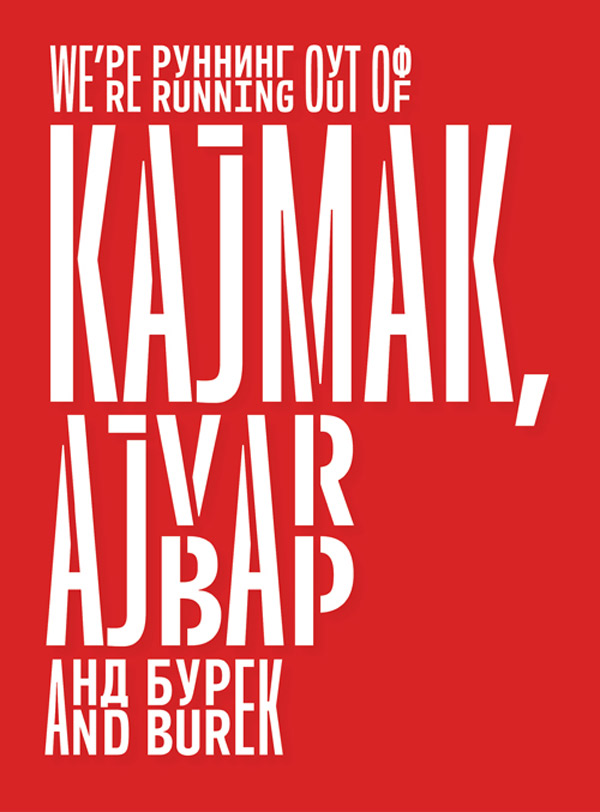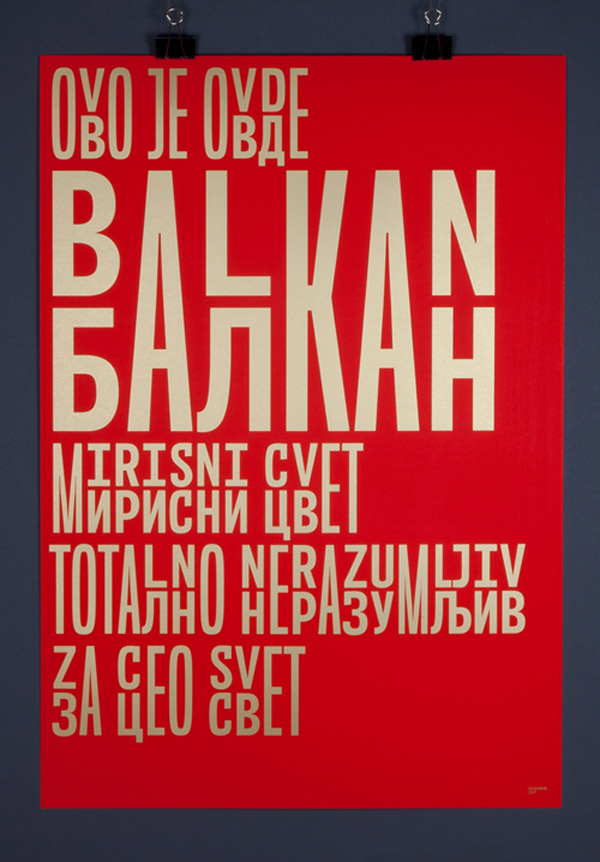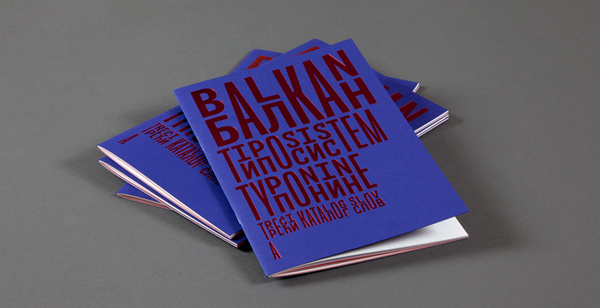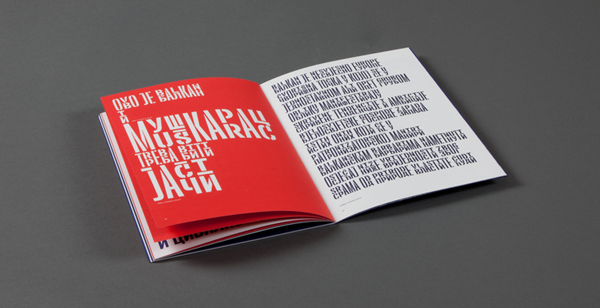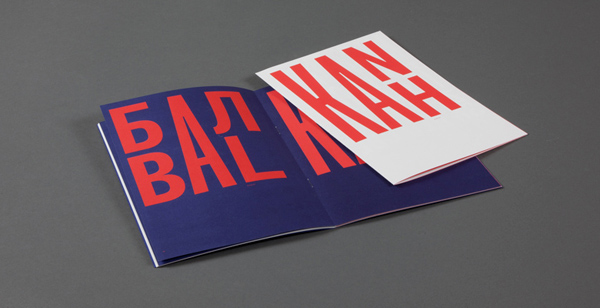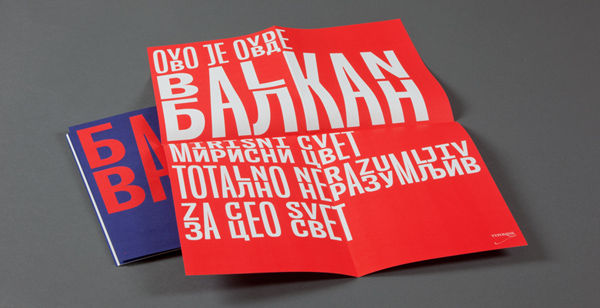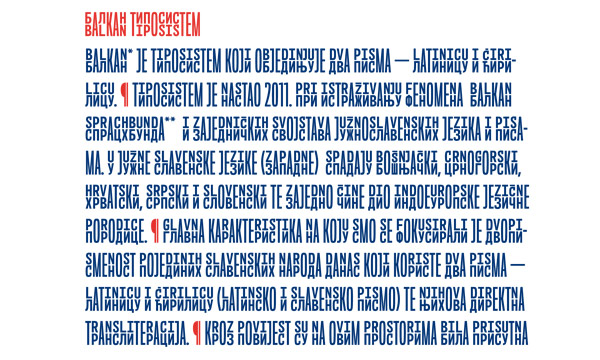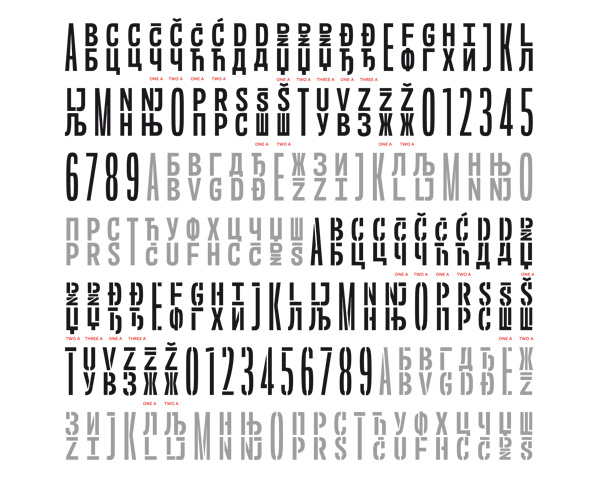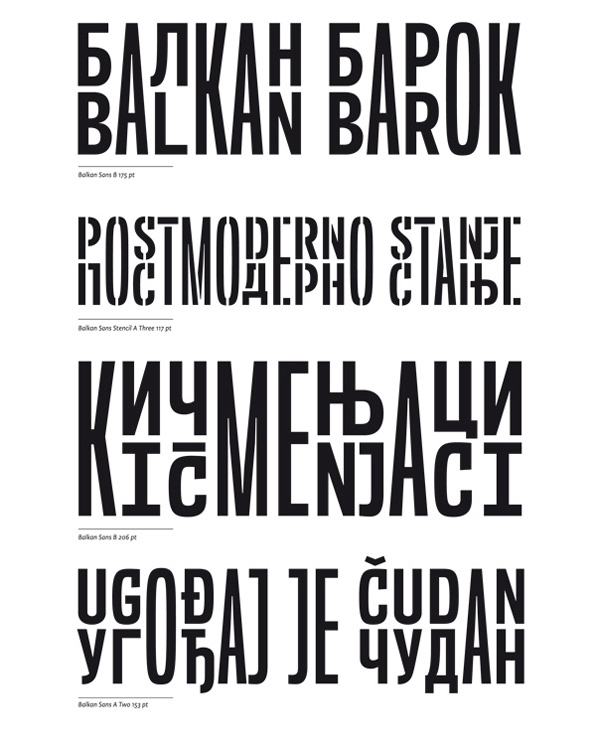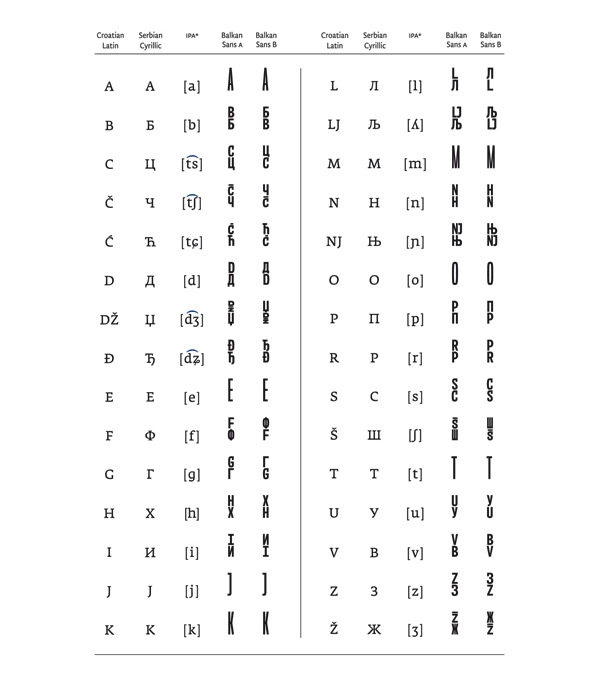
La península de los Balcanes es un territorio habitado por un crisol de etnias, culturas y religiones cuya incomprensión ha derivado, a menudo, en una historia problemática y sangrienta. Con el fin de cauterizar estas heridas, el estudio croata Babushke ha diseñado Balkan, una tipografía que combina los alfabetos cirílico y latino para fomentar la comprensión hacia las culturas vecinas y subrayar su herencia compartida sin menospreciar sus características individuales.
Aplicación tipográfica, Balkan, Babushke, 2012.
Cada una de las lenguas que componen el área lingüística balcánica (bosnio, montenegrino, macedonio, albanés, serbocroata, búlgaro, rumano), aunque diferentes entre ellas, poseen rasgos gramaticales y semánticos que revelan un patrimonio cultural común y una fuerte interacción lingüística. Los últimos acontecimientos históricos han tendido a polarizar las lenguas: “Nuestra intención es desmitificar, despolitizar y reconciliar las diferencias por el bien de la educación, la tolerancia, y especialmente, la comunicación”, apuntan desde el estudio.
Tabla de equivalencias entre caracteres cirílicos y latinos, Balkan, Babushke, 2012.
Balkan Sans y Balkan Stencil, Babushke, 2012.
Aplicación tipográfica, Balkan, Babushke, 2012.
El estudio croata Babushke, integrado por los diseñadores Marija Juza y Nicola Djurek, ha creado una tipografía híbrida que combina los diferentes rasgos lingüísticos de la región. Cada uno de los glifos se compone de un mismo fonema expresado en los sistemas alfabéticos latino y cirílico. Las dos letras se organizan en líneas horizontales paralelas, de tal manera que se establece un texto dual que permite apreciar las semejanzas y diferencias entre los dos abecedarios. En los casos en los que los dos sistemas compartan un mismo símbolo, el glifo se representa con un único carácter que ocupa las dos líneas.
Balkan Sans y Balkan Stencil en sus cuatro modalidades, Babushke, 2012.
Balkan se compone de dos familias tipográficas diferentes: Balkan Sans y Balkan Sans Stencil. Cada una de ellas se subdivide a su vez en dos fuentes en donde se combinan las cajas altas y bajas. La tipografía, aunque limitada a los alfabetos cirílicos y latinos, ha sido pensada para ser expandida a otros sistemas alfanuméricos como el ruso, el macedonio o el búlgaro, siempre con una intención educativa y reconciliadora.
Aplicación tipográfica, Balkan, Babushke, 2012.